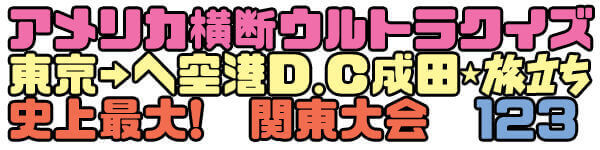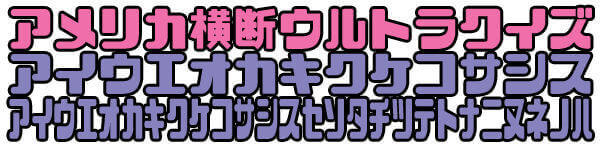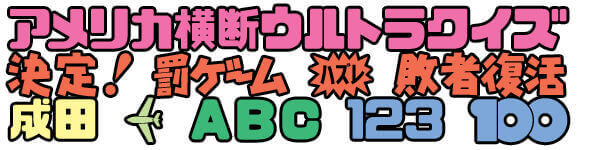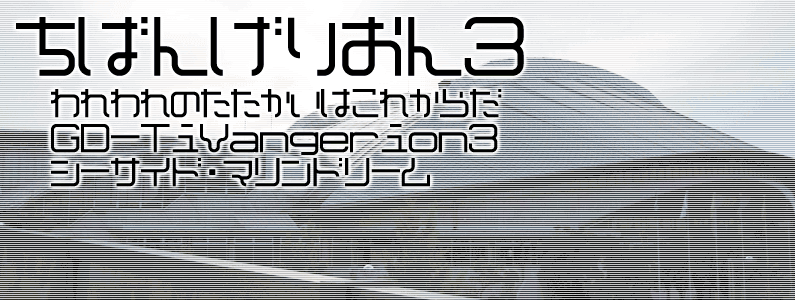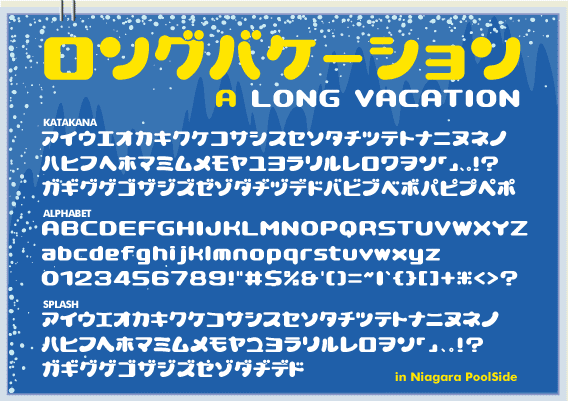
6つ子フォント
作者様いわく某六つ子があまりに可愛いから作ったというフォント。
GD-TiVangerion3-JA
千葉県をPRするロゴマークをモチーフにしたフォント。
Ultra Seven-AL
フォント名のULTRA SEVENという名前の通り、7ポイントの倍数推奨のビットマップフォント。
アストロ 2.0-KT
テレビ朝日で放送されているSmaSTATIONの番組内で使われているカタカナフォント。
ガヴァドン Ultra-KT
怪獣名のロゴに使われそうなデザインのフォント。
クイズフォント「QUIZ SHOW」
ウルトラクイズの各種ロゴを再現したフォント。
クイズフォント「U-Fo」
チェックポイント表記に特化したカナ書体。
クイズフォント「THE 横断」
タイトルロゴに特化したカナ書体。
けいふぉんと!
『けいおん!』のロゴタイプをヒントに作成したフォント。
チェックポイントフォント
ウルトラクイズ風・和文総合書体。
やなせたかし一フォント
やなせたかし先生の文字をフォント化したもの。
ロングバケーションフォント
丸っこくかわいらしいカナ・英数字フォント。
ワンピースフォント
人気アニメ『ワンピース』で使われていいそうな雰囲気のフォント。
自由の翼フォント
TVアニメ『進撃の巨人』第二期オープニングテーマで使用されている書体を真似て作られたフォント。
銀魂 次回予告体(大甘書道体)
アニメ銀魂で次回予告に使われていた文字をデジタルフォント化したもの。